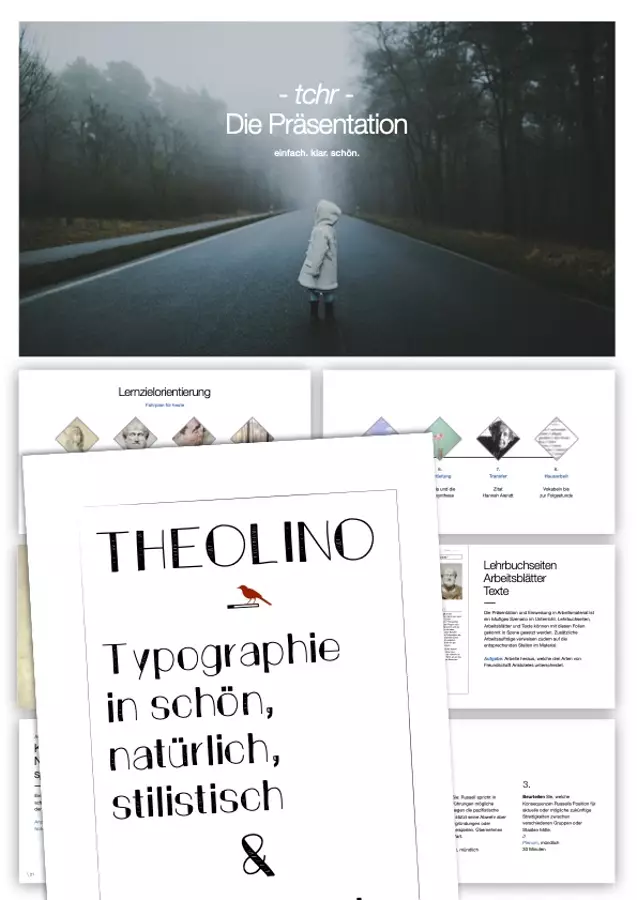Vorschau - Stundenentwürfe - Präsentationsvorlage im Unterrichtsformat für Keynote (macOS) mit typographisch schöner Schriftart "Theolino" - Deckblatt
• dezente Gestaltung der Layouts mit klarem Schriftbild und markanter Typographie
• Schriftart Theolino
Präsentationsvorlage im Unterrichtsformat für Keynote (macOS) mit typographisch schöner Schriftart "Theolino"
Schriftart Theolino (zur kommerziellen Nutzung)
Stilvolles Layouten in schön. Durch einen Hauch „Handschrift“ lassen sich mit Theolino wunderbar typographische Akzente setzen, die Lehr- und Lernmaterial lebendig aufwerten. Dabei überzeugt Theolino auch in Kombination mit anderen Schriftarten (Arial, Helvetica, Georgia etc.) und trägt so zum individuellen Charakter der gestalteten Materialien bei. Und das ist im Paket enthalten: Alle gängigen Zeichen (siehe Vorschau) Beispiele zur Inspiration Schriftart als *.ttf Zur kommerziellen Nutzung auf Lehrermarktplatz gestattet (ausführliche Lizenzbestimmung findest du im Paket)